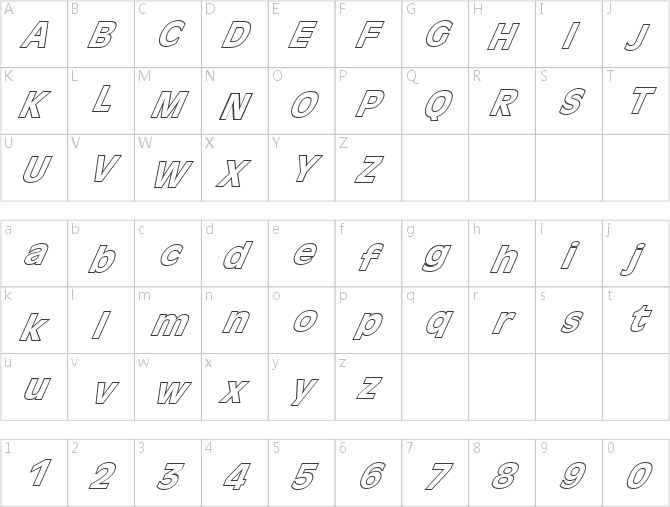
FZ BASIC 1 HOLLOW ITALIC
FZ BASIC 1 HOLLOW ITALIC介绍
FZ BASIC 1 HOLLOW ITALIC字体字库是一款让人赏心悦目、百看不厌的英文字体,适合各类广告和产品包装设计应用,字体大小0.07MB,格式为ttf字体,上传用户是lvpyt,作者/版权方为未知